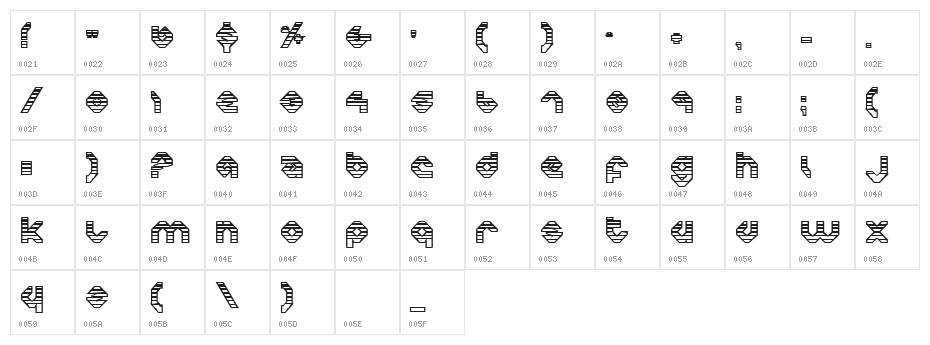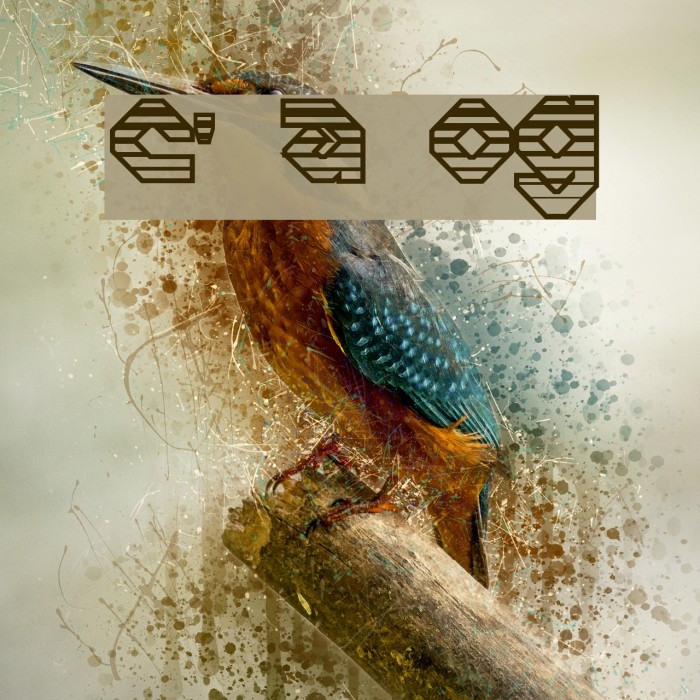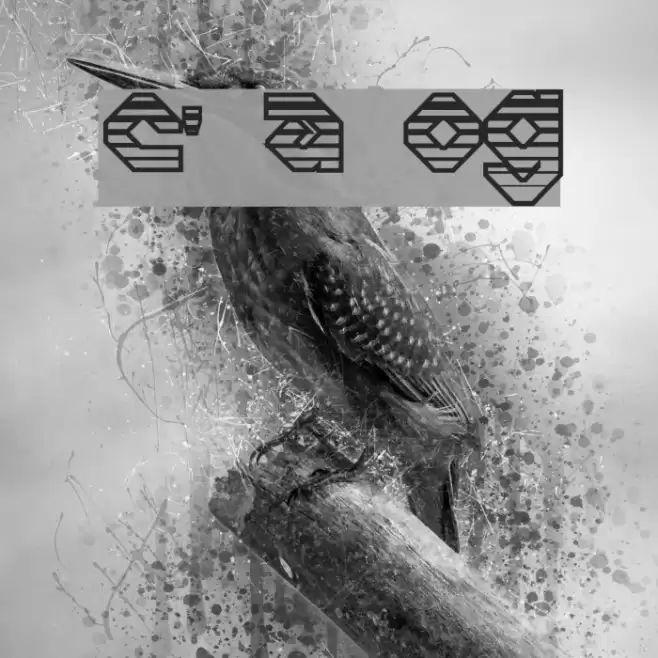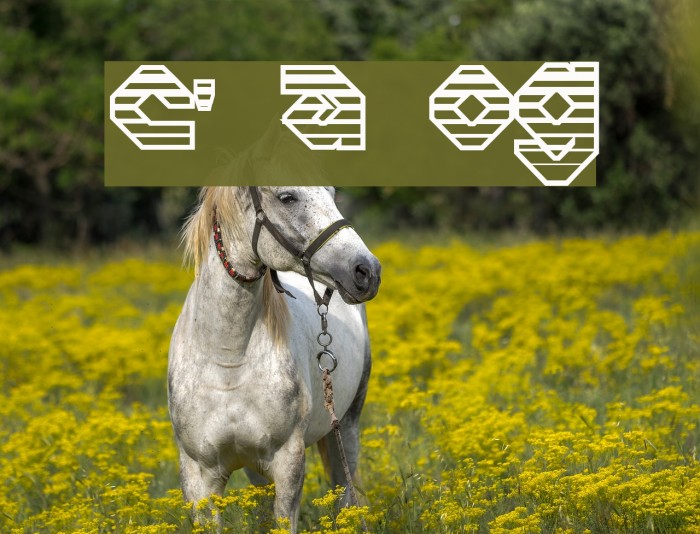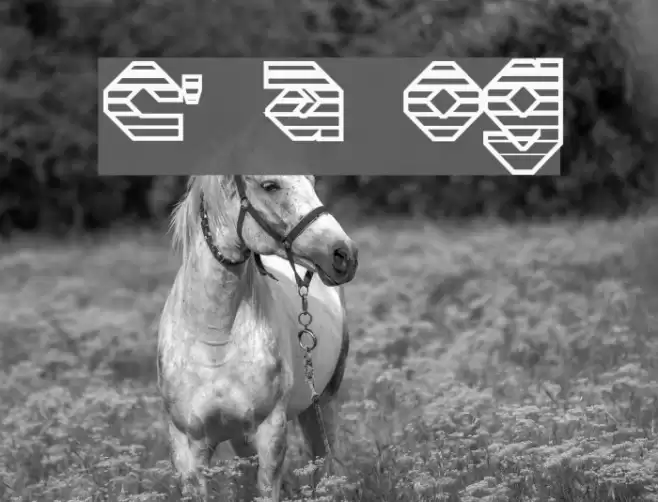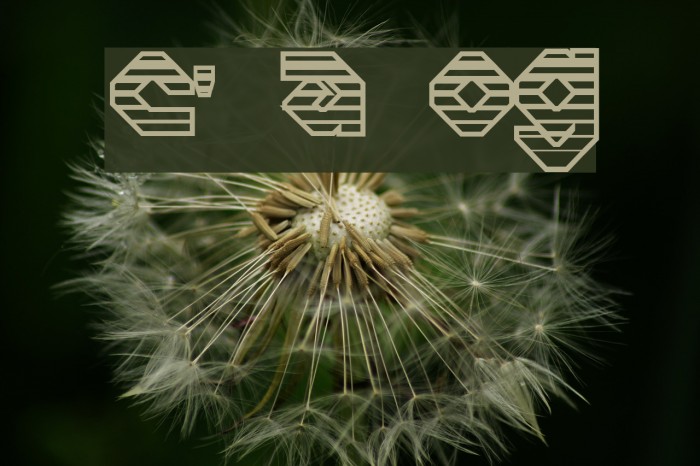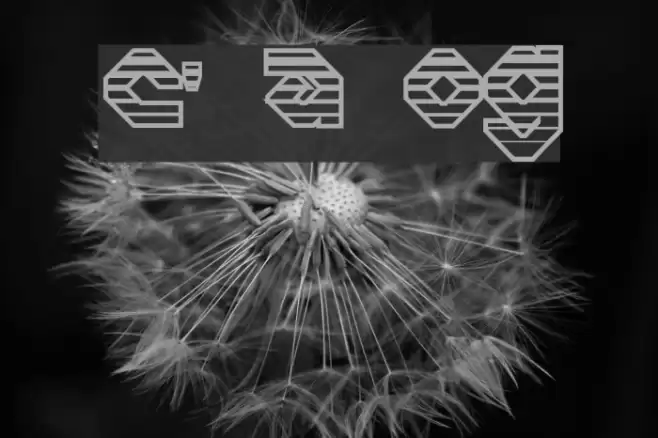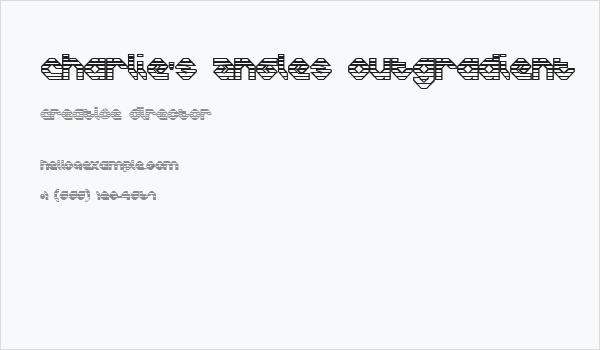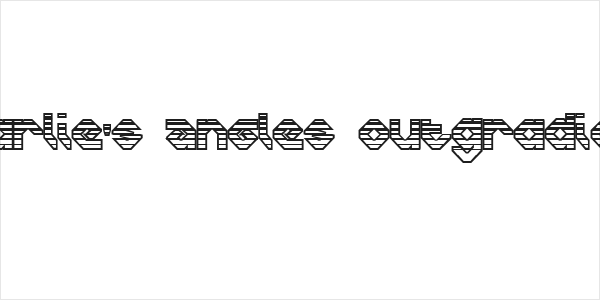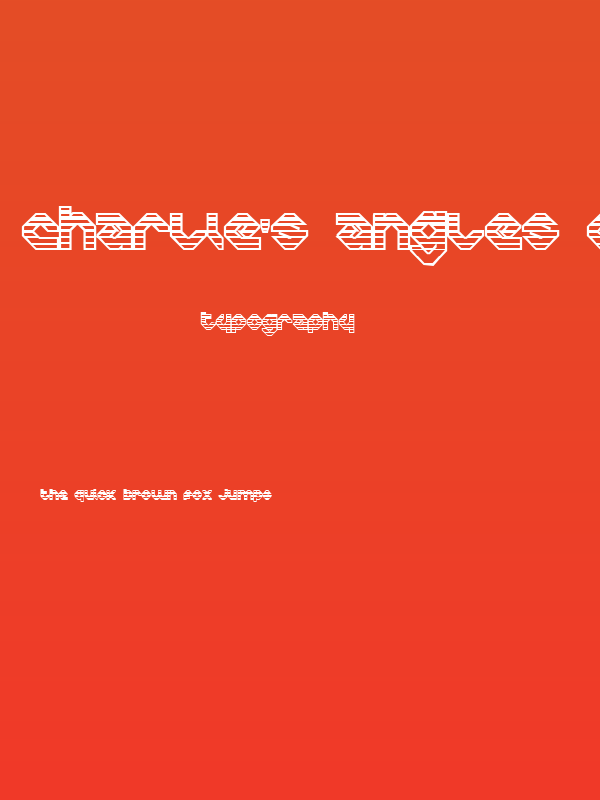
Charlie's Angles OutGradient Font
| Gesamtstil | Futuristic, Decorative |
| Vorgeschlagene Projekte | Ideal for modern posters, album covers, or branding that requires a standout, futuristic look. |